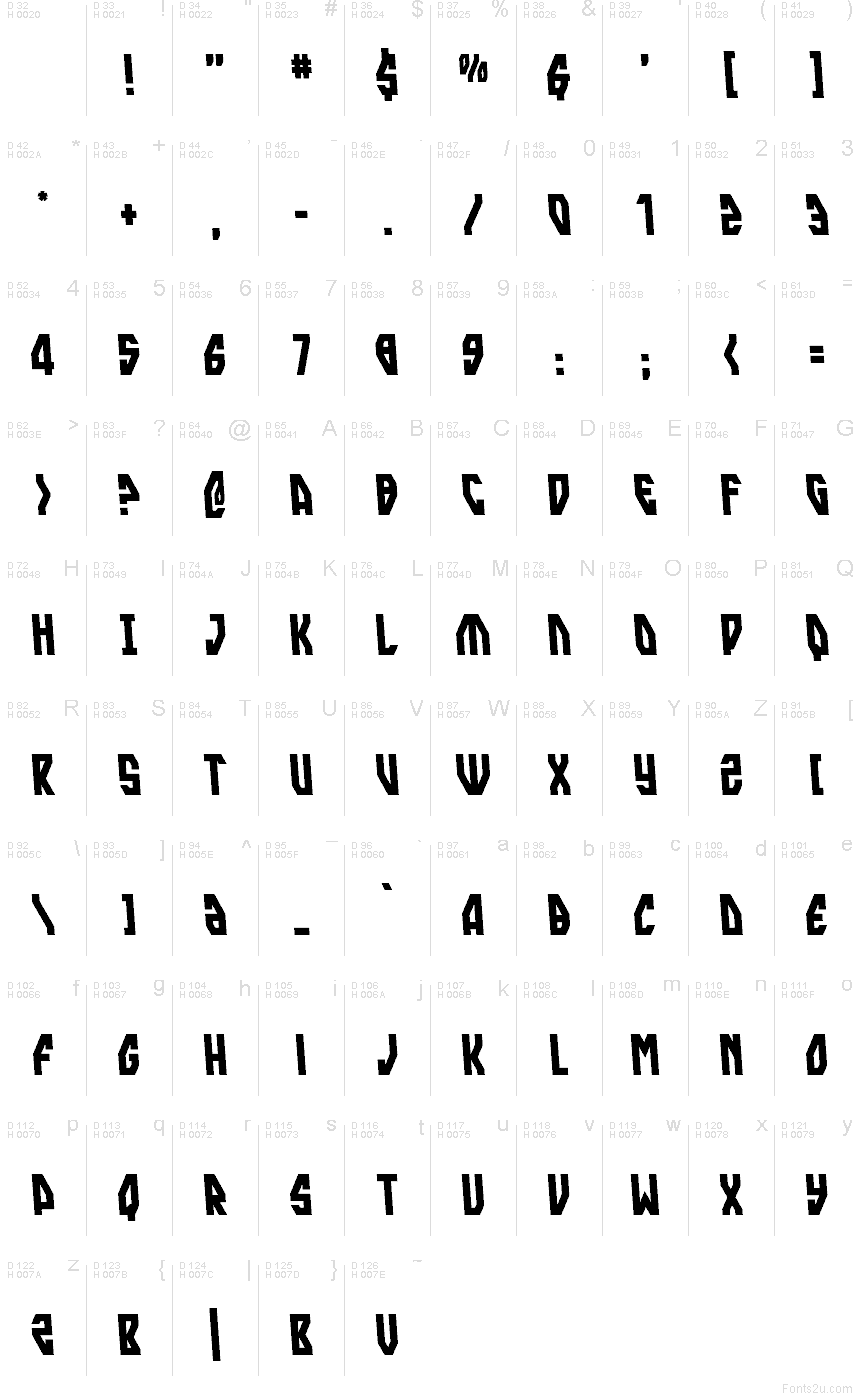
Skyrange Semi-Leftalic od Daniela Zadoroznyho z Iconian Fonts ze stejnojmenné rodiny Skyrange je bezplatné techno písmo. Jeho zubaté, do sebe zapadající tvary působí jako řezané laserem a jsou lehce nakloněné, připomínající kovové značení pro futuristické chodby. Těsné rozestupy a ostrý rytmus dodávají nadpisům okamžitý dynamický náboj bez potřeby dalších efektů.
Se Skyrange Semi-Leftalic dosáhnete úderných výsledků na plakátech se sci-fi tematikou, v esportovém brandingu, u herních UI titulků, letáků na technologické akce, streamovacích overlayích, obalech alb i balení gadgetů. Toto bezplatné písmo vynikne při větších velikostech, kde si zachovává ostrost svých úhlových výřezů. Pro hlavní text ho kombinujte s čistým geometrickým bezpatkovým písmem běžné tloušťky, aby působil klidně a čitelně.